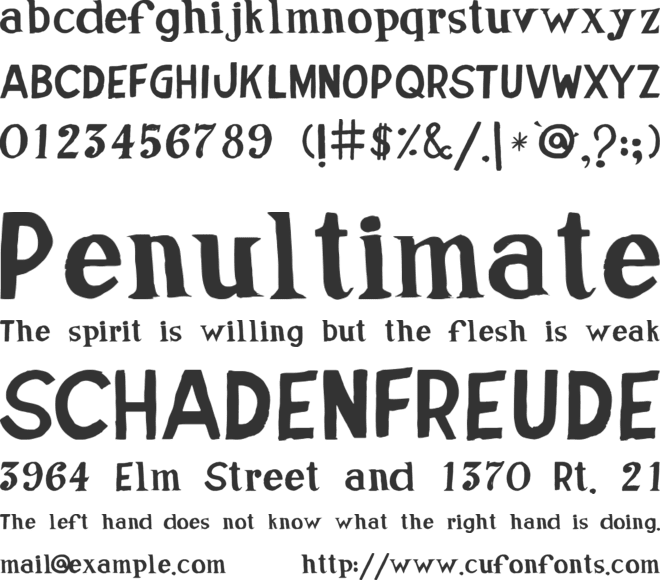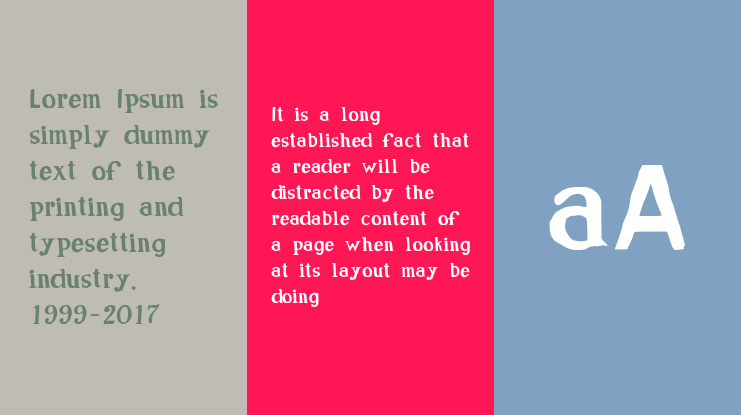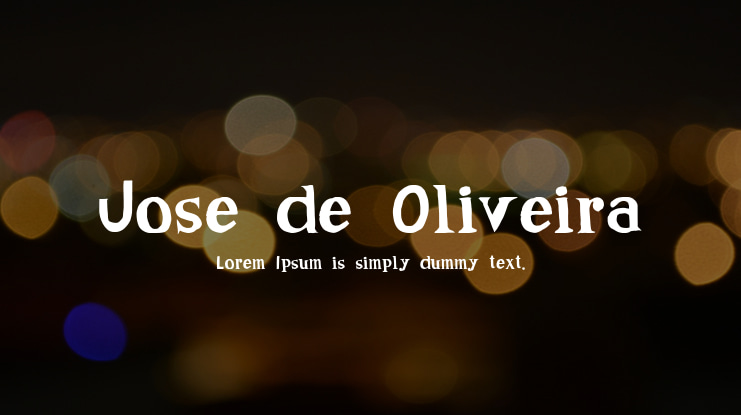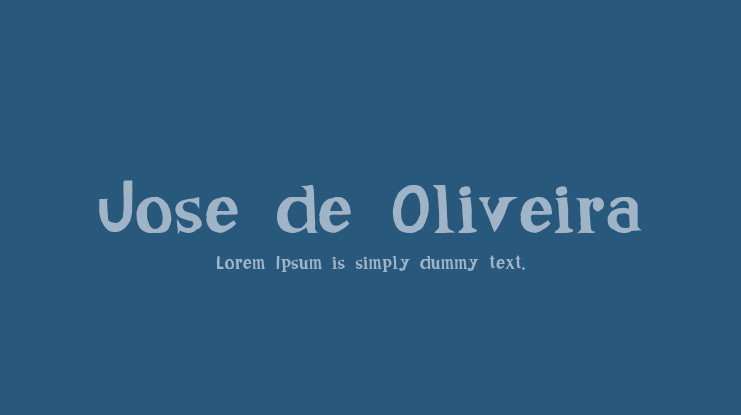
Jose de Oliveira Font Family
Olá Planeta Terra!
Essa fonte feita a mão por José de Oliveira, pintor profissional e cineasta amador nascido na cidade de São Carlos, interior do estado de São Paulo, Brasil. E digitalizada por Árvore Amarela Design Visual, dupla de dois metidos a designers, que vivem no Rio de Janeiro, Brasil (www.arvoreamarela.art.br). Ela foi criada para o filme Delírios de um cinemaníaco e agora está disponível na internet para ser distribuída gratuitamente. A fonte JOSE DE OLIVEIRA de JOSÉ DE OLIVEIRA e ÁRVORE AMARELA foi licenciada com uma licença Creative Commons - Atribuição - Não Comercial - Compartilha Igual 3.0 Não Adaptada. Podem estar disponíveis autorizações adicionais ao âmbito desta licença em http://www.deliriosdeumcinemaniaco.com . Mais informações sobre essa licença em http://creativecommons.org/licenses/by-nc-sa/3.0/deed.pt
Jose de Oliveira font preview
Jose de Oliveira Regular font